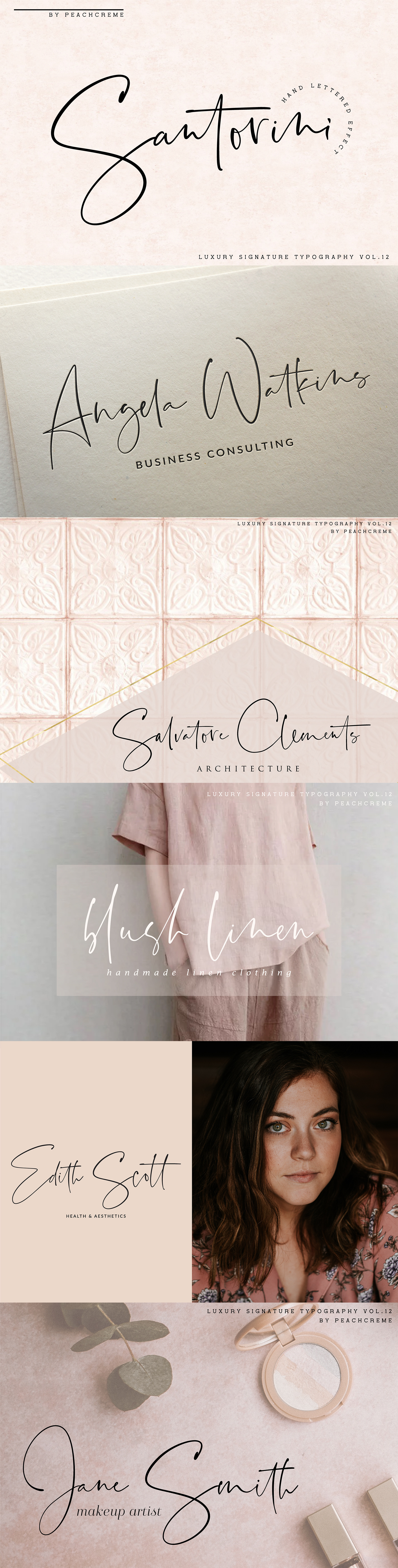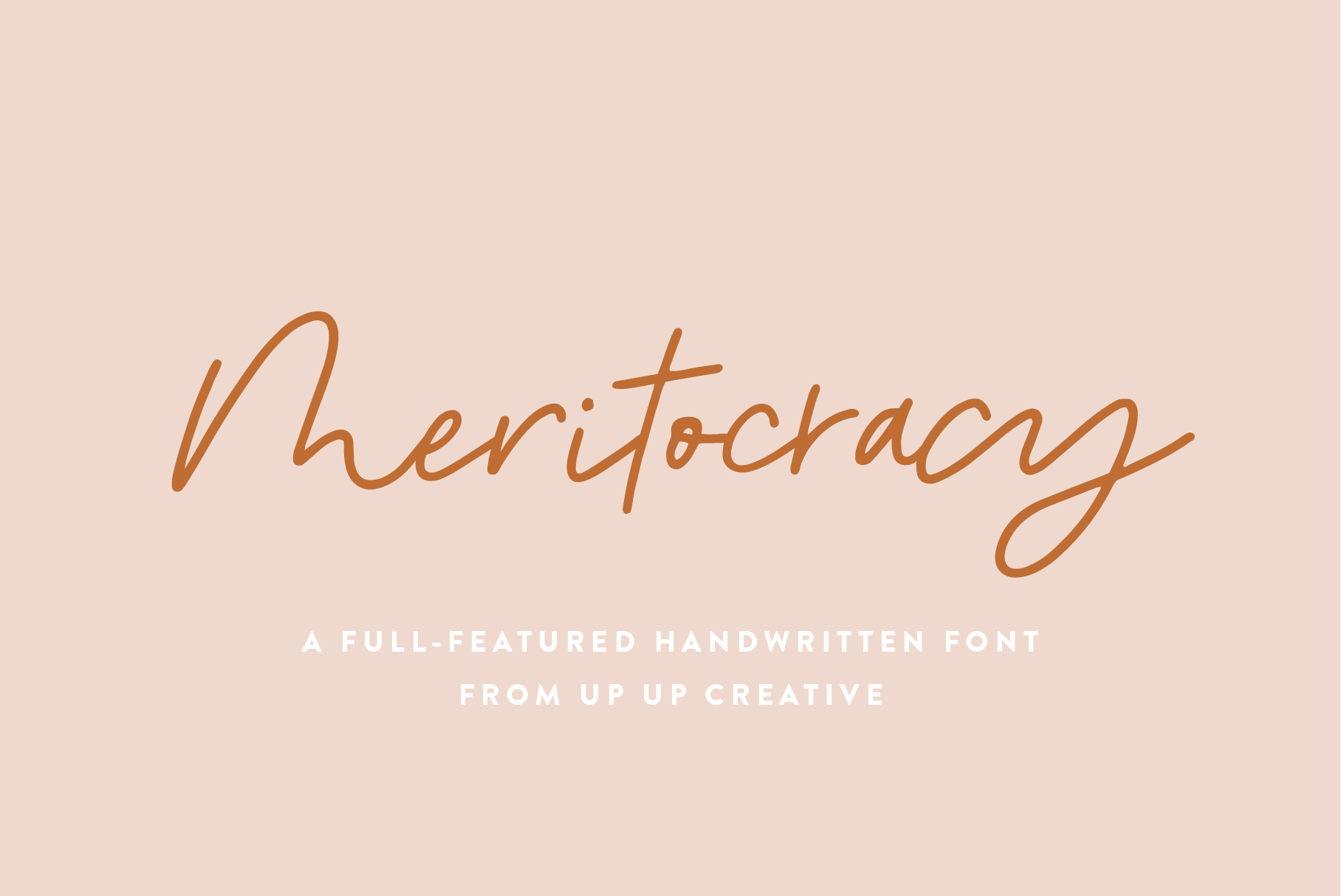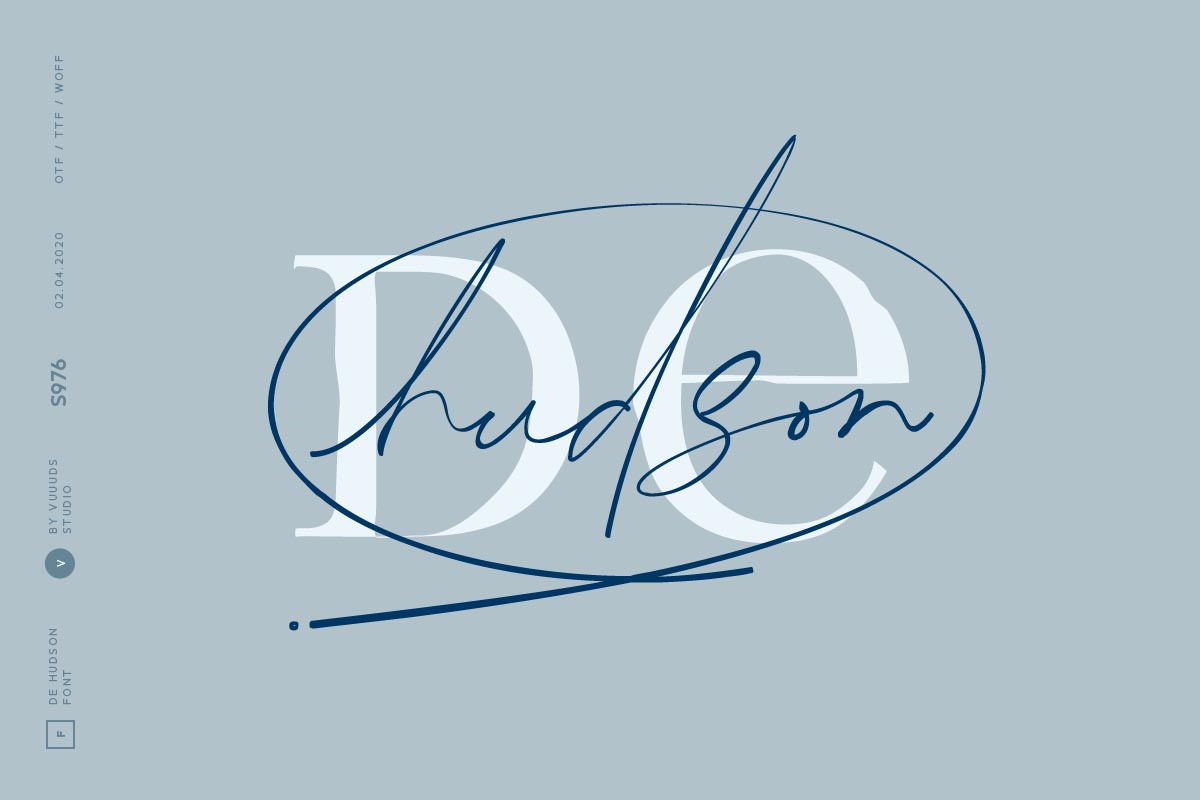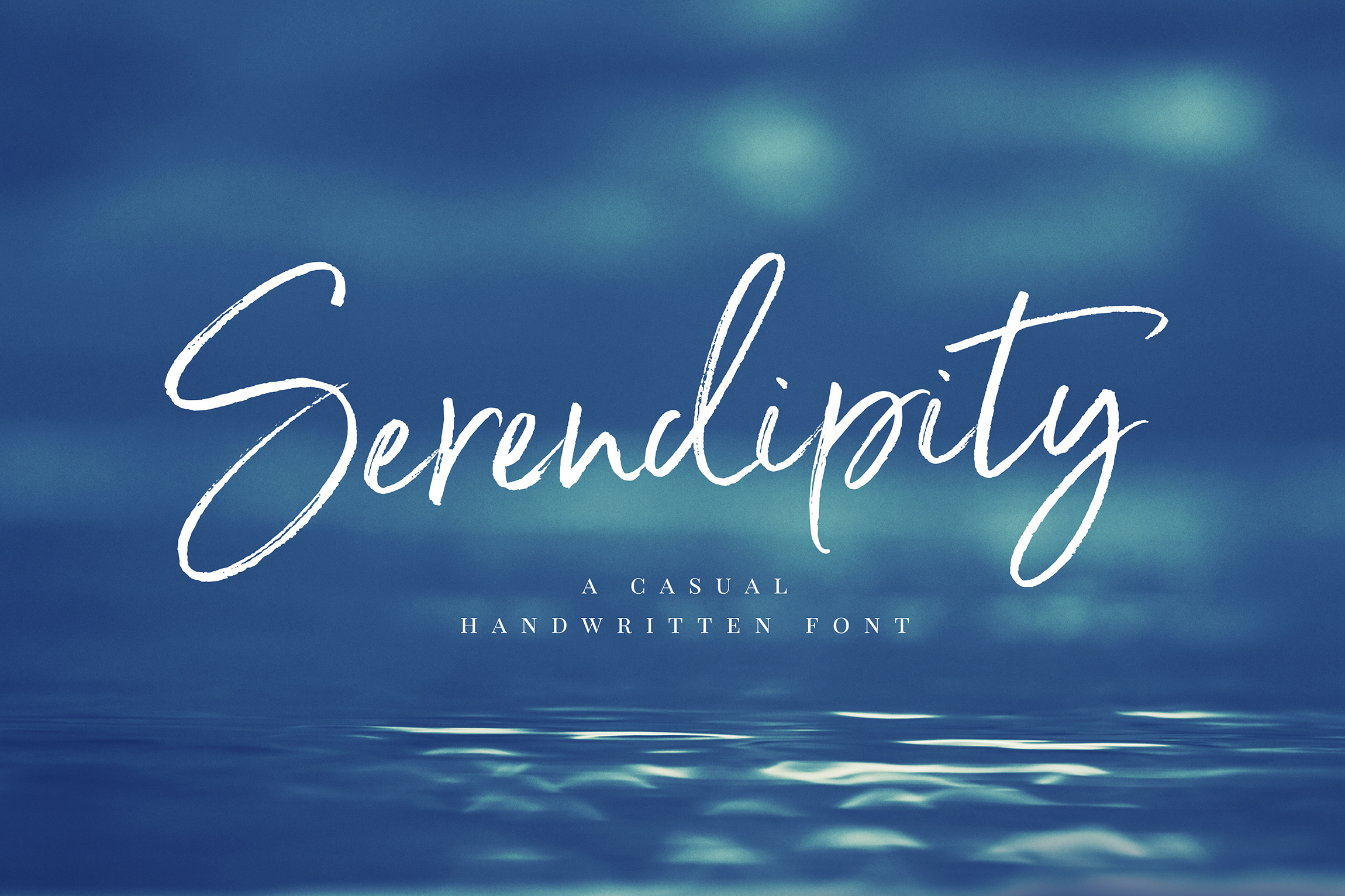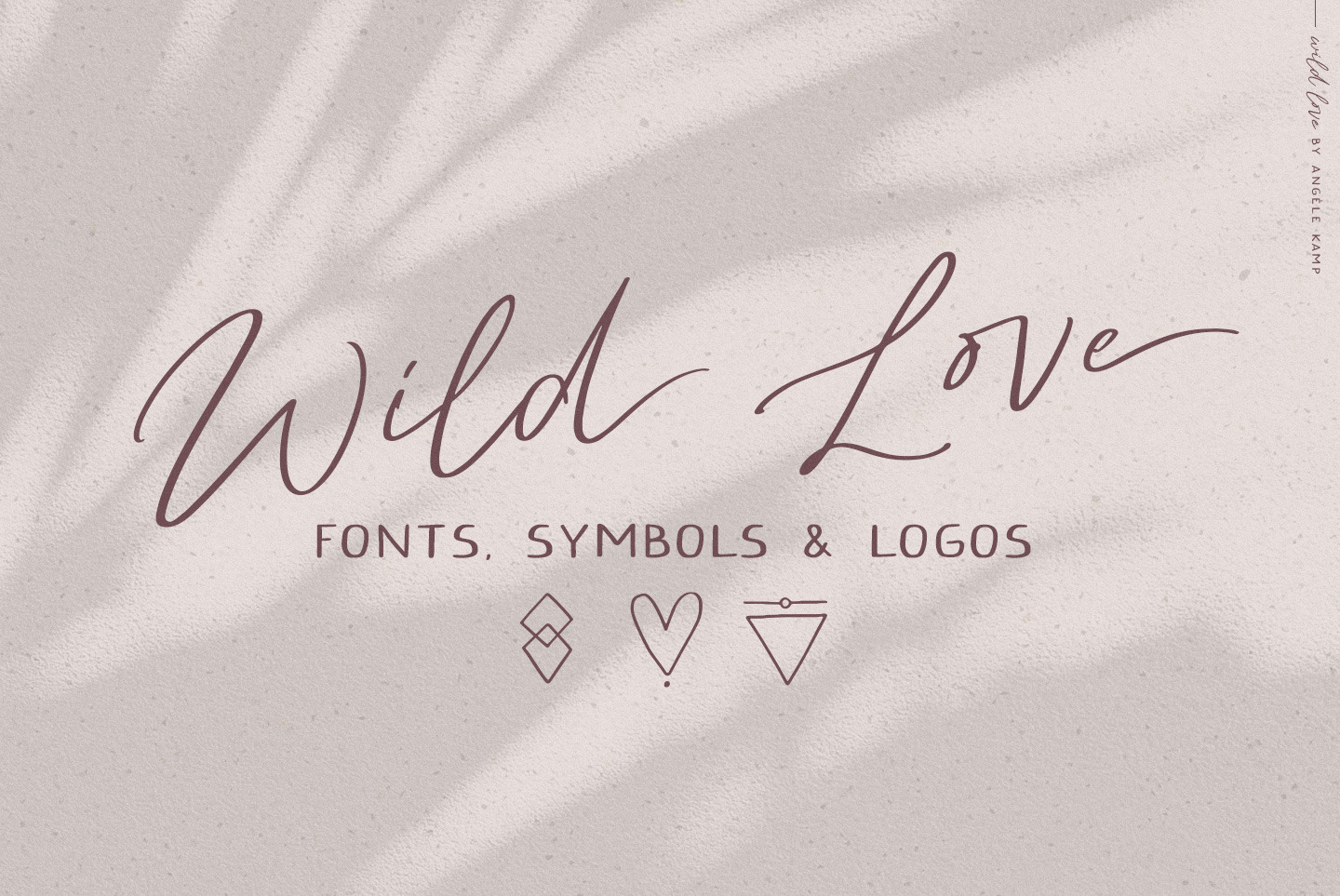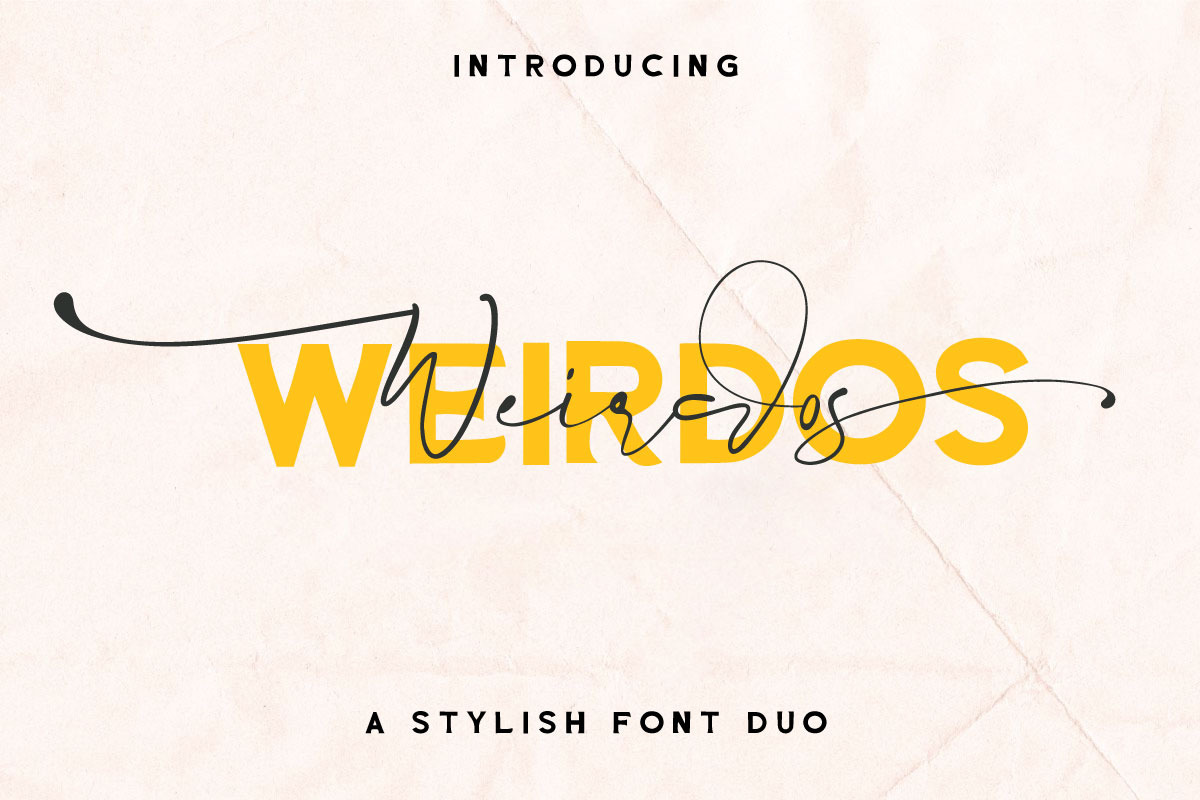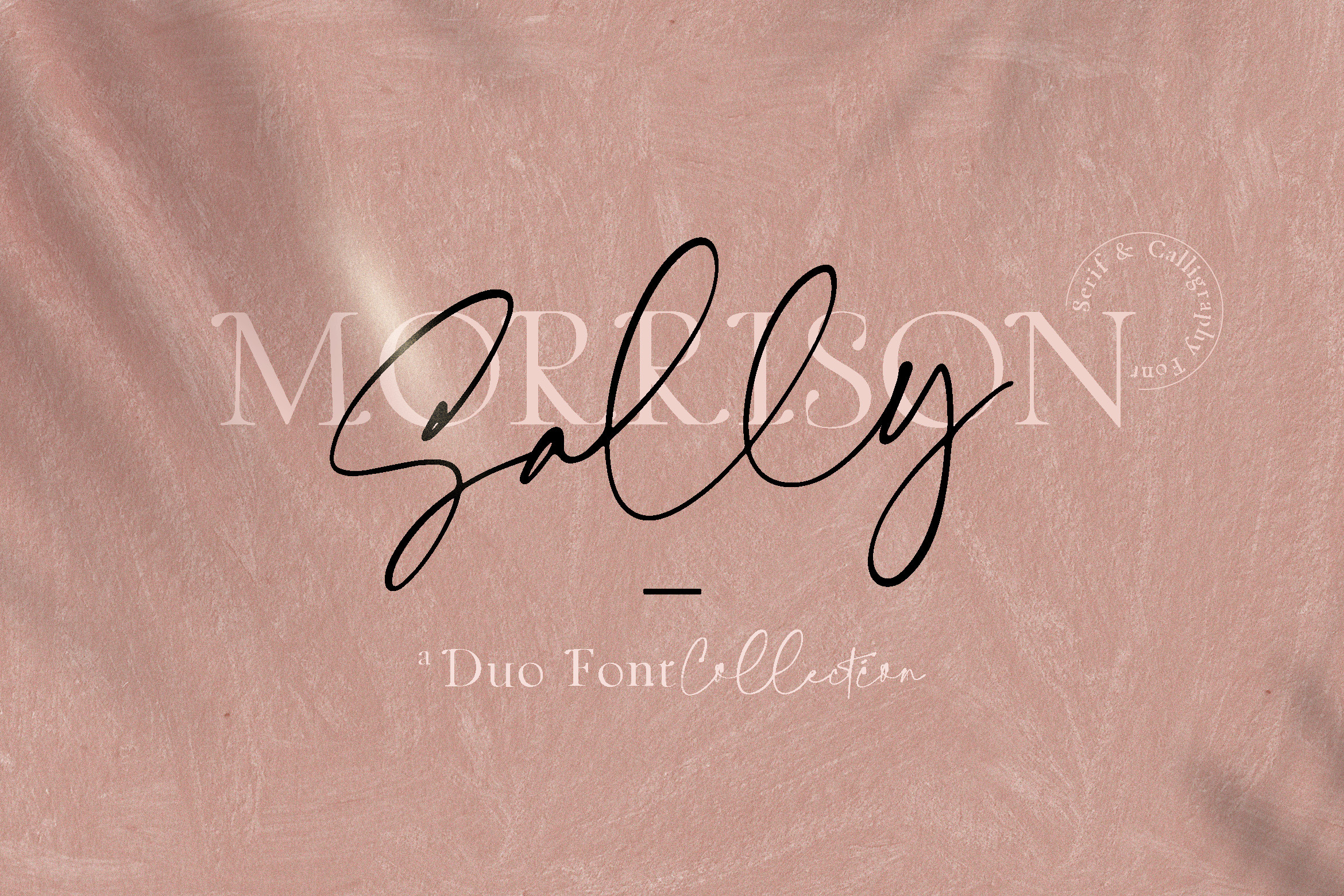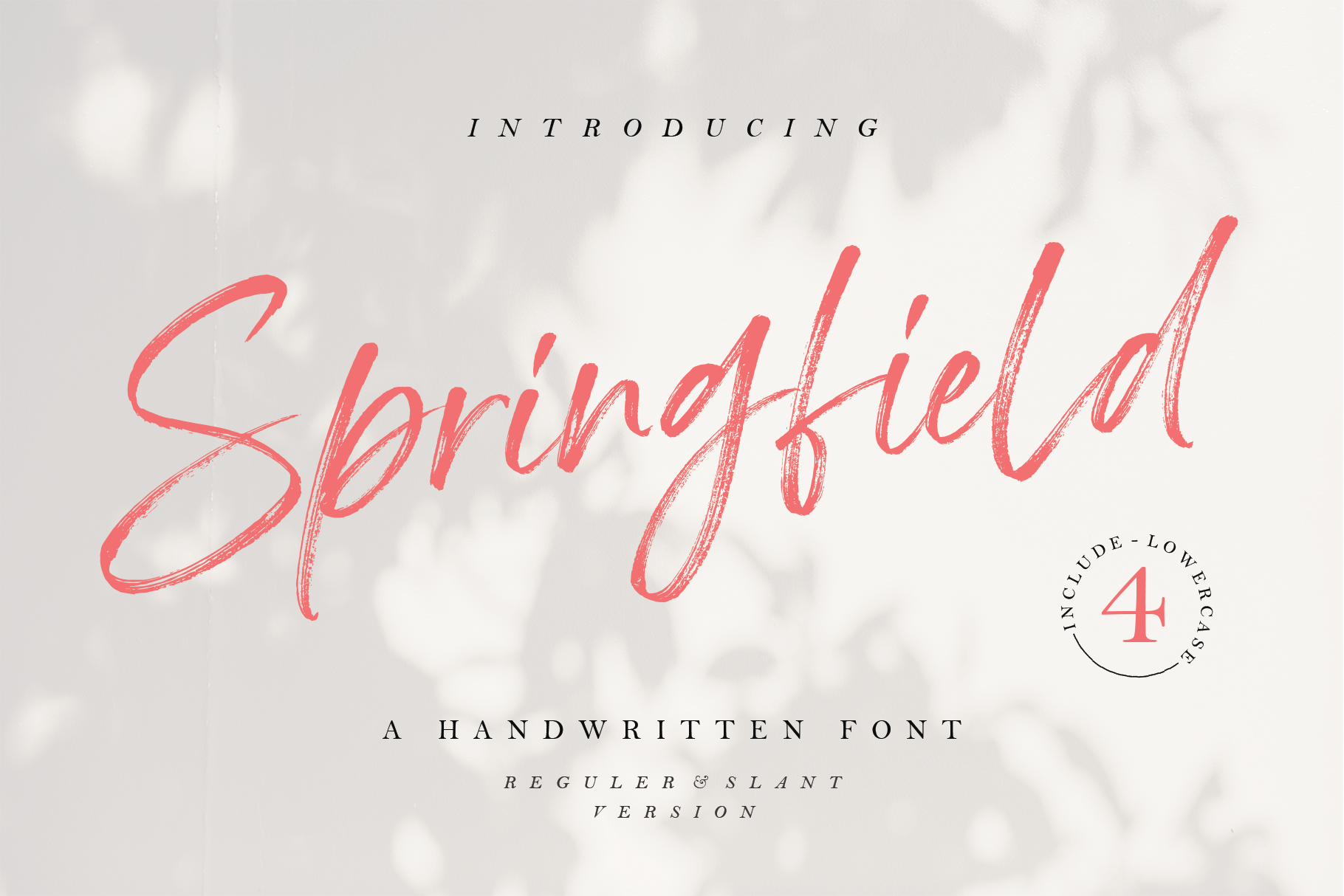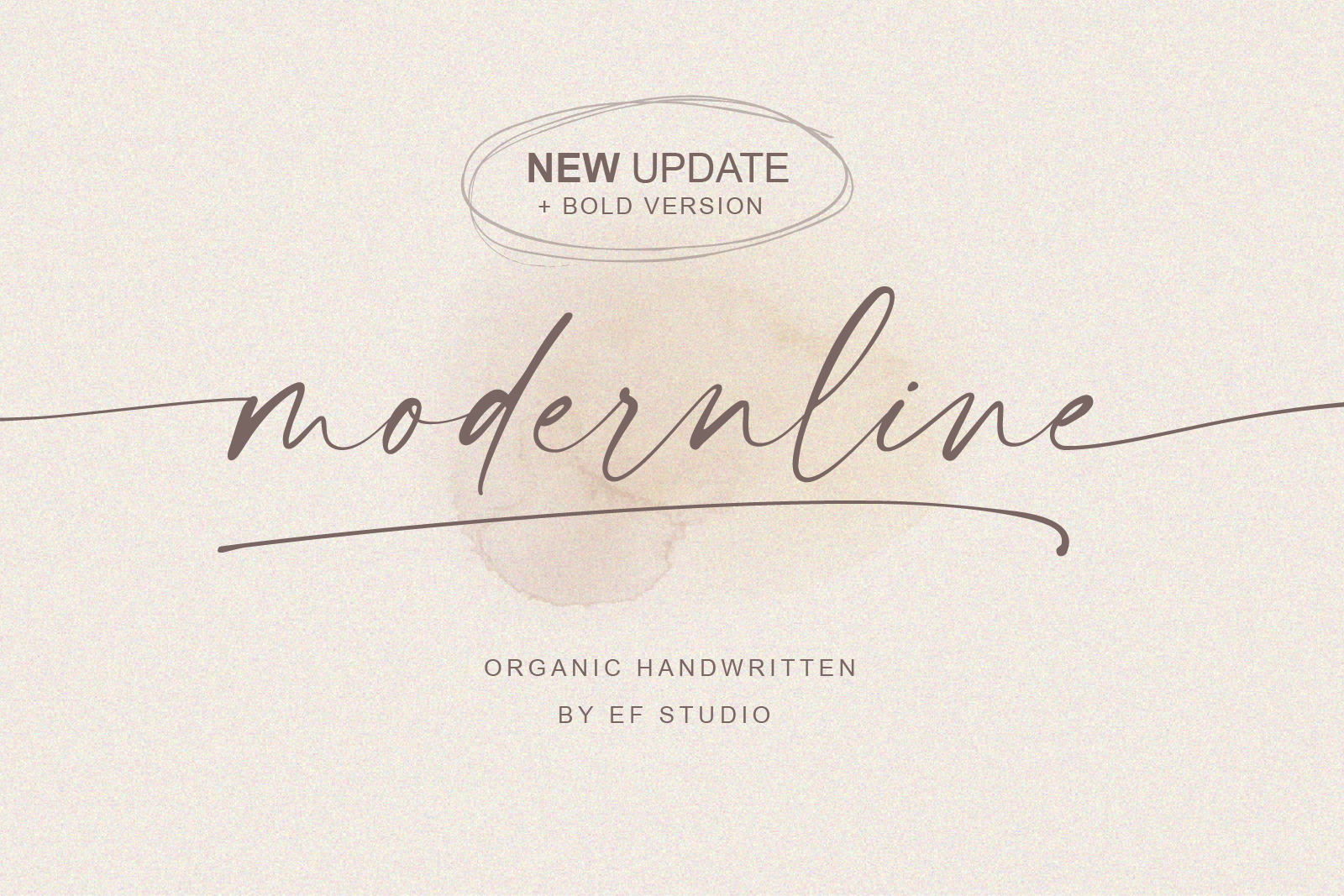
Handlettering-Schriften haben oft einen verspielten, informellen Hauch. Aber auch wenn dein Design einen edlen Touch haben soll, passen sie super - wenn du sie nur schick kombinierst.
Los geht’s mit den außergewöhnlichen Premium-Schriften - egal, ob du eine Website, Hochzeitseinladungen oder ein Cover für dein Bullet Journal planst!
Schriftart Santorini*
Eine tolle Handlettering-Schrift mit ausdrucksstarken Lettern, perfekt für Logos oder edle Einladungs-Cover. Ich mag bei der Santorini-Schrift* besonders die Mischung aus runden Buchstaben und dem edgy Schriftfluss.
Schriftart Sophia & Ronald*
Love is in the air!
Wenn es bei deinem Projekt oder Branding romantisch hergehen soll, ist diese Schrift* (mit Option zu Herzchen!) im Handwritten Style perfekt.
Schriftart Springfield*
Sehr schön schwungvoll, ohne zu wild auszusehen: Springfield* ist eine tolle Handschrift mit einem Touch Boho-Look.
Die einzelnen Buchstaben sehen wie gemalt aus, fließen schön ineinander und haben einen Pinselstrich-Look.
Schriftart Meritocracy*
Meritocracy* ist eine ziemlich moderne, jugendlich aussehende Handwriting-Schrift. Perfekt, wenn der Look etwas cleaner, aber trotzdem ausdrucksvoll sein soll.
Schriftart Serendipity*
Hier kommt alles zusammen: Bei der Schrift Serendipity* bekommst du einen edlen Look, schön geschwungene Buchstaben und Lettering-Vibes in einem.
Die Schrift hat auch einen Hauch von etwas Rustikalem an sich und passt super zu modernen Branding- oder Einladungsprojekten.
Schriftart De Hudson*
Edel, elegant, Premium-Look: Das sind die Attribute, die De Hudson* ausmachen. Diese Handlettering-Schriftart ist nicht nur sehr luxuriös, sondern hat meiner Meinung nach auch etwas ganz Eigenes.
Außerdem sind im Paket gleich drei Schriftarten enthalten - davon auch eine mit Serifen als kontrastreiche Kombinationsschrift.
Schriftart Wild Love*
Leicht bohemian, ungezähmt, verspielt und trotzdem sehr elegant ist Wild Love* eine Schriftart, die sogar mit kleinen Symbolen zur Logo-Kreation daher kommt.
Schriftart Weirdos Font duo*
Ein Font-Duo mit moderner Note: Weirdos* ist eine Kombination aus einer handgeschriebenen und einer Serifen-Schrift, die einen neuen Look mit Schnörkeln kombiniert.
Schriftart Sally Morrison*
Sally Morrison* ist ebenfalls ein Schriften-Duo, also eine Kombination, die besonders gut zusammen passt. Das ganze erinnert stark an Kalligraphie und hat einen sehr schön “wilden” Vibe.
Definitiv keine Handwritten-Font für “brave” Projekte, sondern perfekt, wenn es ein bisschen ausdrucksstärker sein soll.
Schriftart Modernline*
Eine schöne organische, edle und ziemlich dynamische Handwritten Schrift: Modernline* ist perfekt für feminine Branding-Projekte, Packaging Design mit Premium-Appeal oder schicke Hochzeitseinladungen.